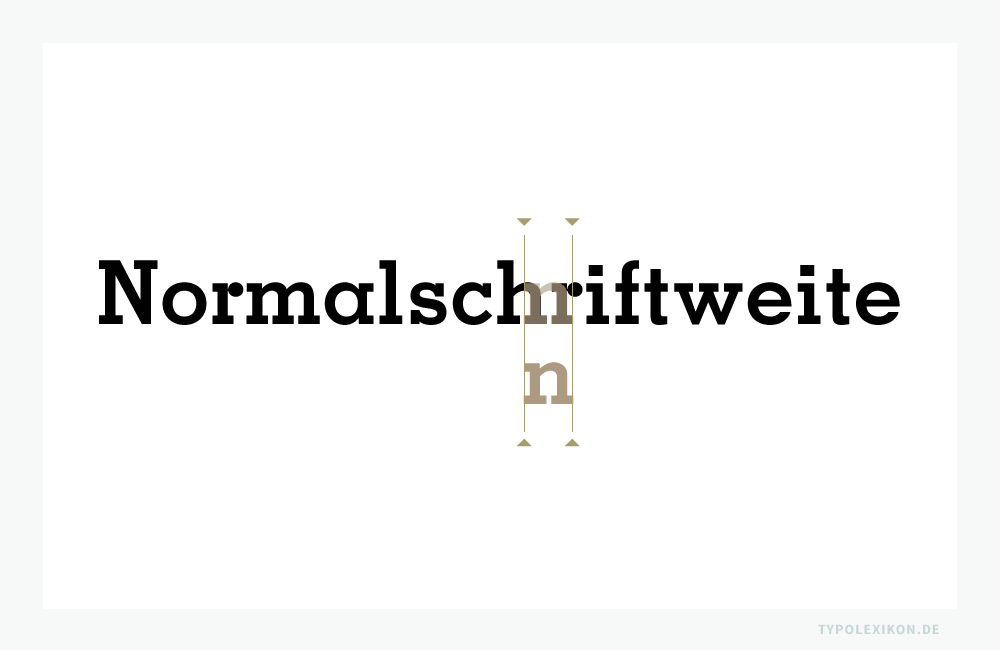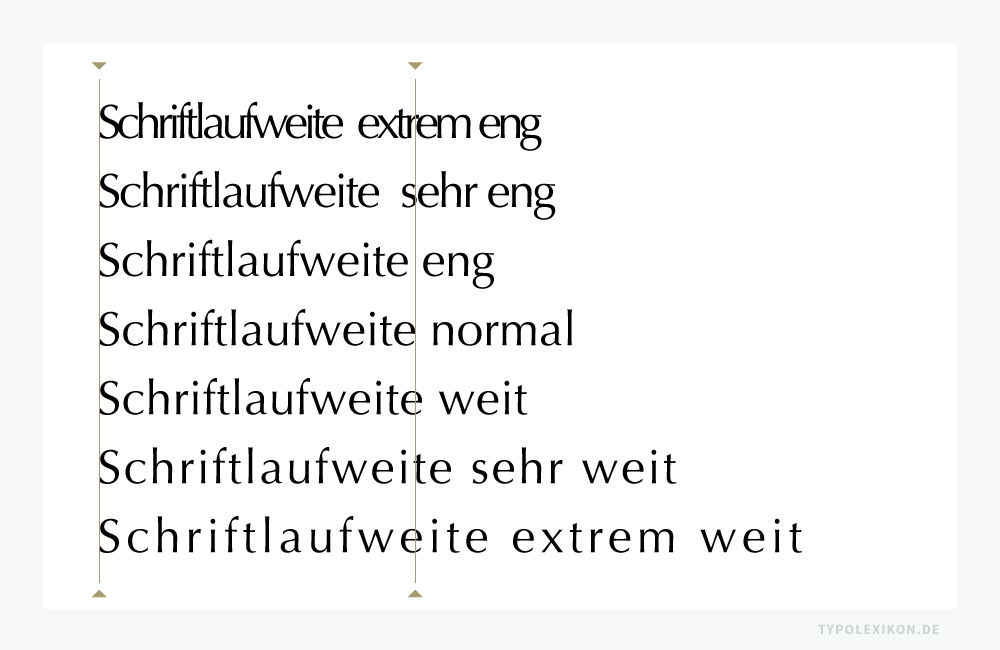
Schriftlaufweite
»Schriftlaufweite« ist ein typografischer Terminus für die Laufweite einer maschinell oder digital reproduzierbaren Schrift, beispielsweise einer Druckschrift oder eines Webfonts; gws. Abk. »Laufweite«; eng. »Letter-Spacing«; CSS-Eigenschaft »letter-spacing«; im materiellen Schriftsatzes mit physischen Drucktypen aus Metall (z.B. aus einer Blei-Zinn-Antimon-Kupfer-Legierung) als »Breitenlauf« bezeichnet.
Unter der Schriftlaufweite wird der systematische Abstand der Buchstaben, Arabischen Ziffern bzw. Schriftzeichen zueinander verstanden. Die Laufweite von Buchstabenpaaren bzw. angrenzenden Schriftzeichen wird als Zeichenabstand (ugs. Buchstabenabstand) bezeichnet. Die positive (+LW) und negative (-LW) Laufweitenveränderung der natürlichen Laufweite (LW 0) einer Schrift gehört in den Bereich der Mikrotypografie.
Eine optimale Schriftlaufweite ist in der Lesetypografie neben anderen mikrotypografischen Parametern ausschlaggebend für die Lesbarkeit eines Wortes, einer Zeile oder einer Textpassage. Sie beeinflusst sowohl im Nahbereich als auch im Fernbereich maßgeblich den Leseprozess (siehe Fixationen), den Grauwert eines Schriftbildes sowie den Satzumfang. Weicht die Schriftlaufweite bei Textschriften (Werksatzschriften) und Display Fonts zu eng oder zu weit von der Normalschriftweite (NSW) ab, wird der Leseprozess erschwert.
Allgemein gültige Werte für eine bestmögliche Schriftlaufweite existieren nicht. Die optimale Laufweite ist immer von der Schriftgattung (z.B. Antiqua-Schrift), Hauptschriftgruppe (z.B. Antiqua mit Serifen), Schriftuntergruppe bzw. Schriftart (z.B. Klassizistische Antiqua), Schriftnebengruppe (z.B. Bodoni-Variante), Schriftlage (z.B. gerade oder kursiv), Schriftbreite (z.B. schmal oder breit) und Schriftstärke (z.B. mager oder fett), Schriftgrad (z.B. als Konsultationsgröße, Lesegröße, Schaugröße oder Ferngröße), vom Ausgabemedium (z.B. Retina-Display), Trägermaterial (z.B. Naturpapier) und der Drucktechnik (z.B. Hochdruck) abhängig.
Werden beispielsweise Textschriften in Fern-, Schau- und Plakatgrößen verwendet, läuft die natürliche Laufweite – also die Normalschriftweite (LW 0) – aufgrund der linearen Vergrößerung oft zu weit. Der Grauwert ist dann meist zu hell und das Schriftbild könnte unleserlich werden. Eine Verringerung (-LW) der Normalschriftweite wäre dann sinnvoll. Andererseits kann die Erweiterung (+LW) der Normalschriftweite bei Textschriften in Konsultationsgrößen, also bei sehr kleinen Schriftgraden, die Lesbarkeit spürbar optimieren.
Normalschriftweite (NSW)
Die natürliche Laufweite einer Schrift – bei physischen Schrifttypen der »Normale Breitenlauf« oder die »Normale Grundschriftweite« bzw. bei digitalen Fonts die »Laufweite Null« (LW 0) – wird als Normalschriftweite (NSW) bezeichnet. Unter der Normalschriftweite versteht man die Schriftlaufweite, die bei physischen Drucktypen durch den natürlichen Breitenlauf bzw. bei digitalen Fonts durch Long- oder Short-Kerning-Tabellen (Relatives Kerning) vom Schriftgestalter:in bzw. Schrifthersteller vorgegeben ist.
Die ideale Normalschriftweite (NSW) hängt von der gewählten Schrift und ihrem Schriftgrad ab. Eine Faustregel besagt, dass sich die NSW an der Punze der Minuskel »n« orientieren könnte. Beispiel gesetzt in der Memphis Bold von Rudolf Wolf (1895–1942), D. Stempel AG, Frankfurt am Main, 1930. Vertrieb über Linotype®. Infografik: www.typolexikon.de
Die ideale Normalschriftweite (NSW) hängt von der gewählten Schrift und ihrem Schriftgrad ab. Eine Faustregel besagt, dass sich die NSW an der Punze der Minuskel »n« orientieren könnte. Beispiel gesetzt in der Memphis Bold von Rudolf Wolf (1895–1942), D. Stempel AG, Frankfurt am Main, 1930. Vertrieb über Linotype®.
Die »Zurichtung« und das »Relative Kerning« 1) von maschinell oder digital reproduzierbaren Schriften hat sich im Laufe der letzten Jahrzehnte aufgrund neuer Schriftsatzsysteme und modischer Ambitionen stark verändert. Normalschriftweiten unterscheiden sich deshalb je nach Schrift, Schriftsatzsystem, Font Foundry und Erscheinungsjahr. Ein wohlproportioniertes Kerning gilt als wesentliches Qualitätsmerkmal eines Fonts. 2)
Optischer Schriftweitenausgleich (OSW)
Wird die Schriftlaufweite einer Zeichenkombination, eines Wortes oder Textes durch eine positive Laufweitenveränderung (+LW) oder Leerraumzeichen erweitert und/oder durch eine negative Laufweitenveränderung (-LW) verringert, wird dies in der Mikrotypografie als »Optischer Schriftweitenausgleich« (OSW) bzw. als »Laufweitenausgleich« bezeichnet.
Differenzierung:
• Wird die Normalschriftweite (NSW) durch eine positive Laufweitenveränderung (+LW) generell erweitert, spricht man von »Spationieren«.
• Wird der Breitenlauf einer physischen Drucktype mit gleich großen Trennfugen bzw. Spatien erweitert, nennt  man das »Sperren«.
• Wird die Normalschriftweite (NSW) durch Leerraumzeichen erweitert, spricht man ebenfalls von »Sperren«.
• Wird die Normalschriftweite (NSW) bei Nichtproportionalschriften (Festbreitenschriften oder Monospaced Fonts) mit Leerraumzeichen erweitert, bezeichnet man das als »Dicktengleiches Sperren«.